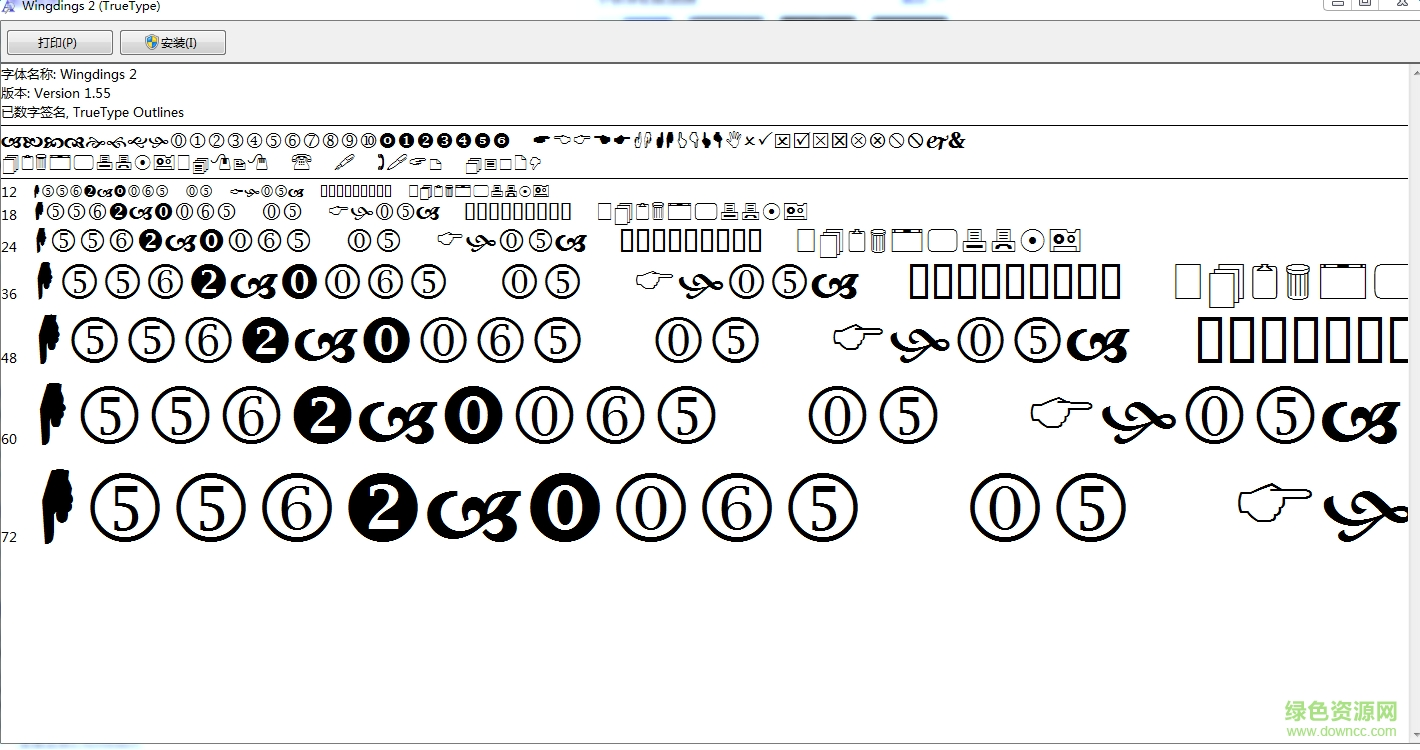
wingdings2字體是一款ttf格式的符號(hào)字體,包含了圈圈、手勢(shì)、信封、書(shū)本、花紋等各種符號(hào),可廣泛應(yīng)用于各種設(shè)計(jì)中,歡迎在綠色資源網(wǎng)下載使用!
Wingdings2字體介紹
Wingdings2是一種TrueType符號(hào)字體,比如在微軟office中預(yù)置的。該字體由Type Solutions, Inc.公司在1990年開(kāi)發(fā)。Wingdings2的規(guī)格中包括了16種索引,字母數(shù)字從0到10的序號(hào),多種記號(hào)和問(wèn)嘆號(hào),幾個(gè)幾何形狀和星形。該字體沒(méi)有被編入U(xiǎn)nicode。